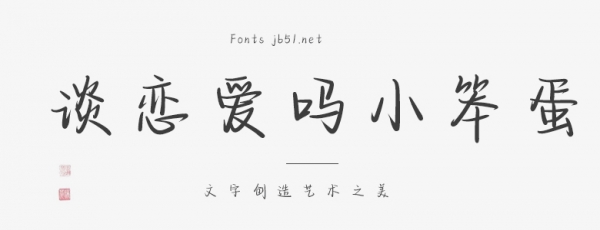
談戀愛嗎小笨蛋字體是一款充滿浪漫與情感的藝術(shù)字體。該字體設(shè)計靈感來源于戀愛中的甜蜜與純真,將每一個字母、符號都融入了溫馨、趣味的元素。 字體線條流暢,字母之間的距離適中,視覺效果舒適。每個字母都帶有柔和的曲線,仿佛戀人的微笑一般甜美。特別地,小寫字母“a”的頂部設(shè)計成了一個小小的愛心,表達出對愛慕之人的深深愛意。 整款字體風(fēng)格清新、俏皮,適合應(yīng)用于各種浪漫、溫馨的場合,如情侶間的書信、禮品包裝、婚禮請柬等。當(dāng)使用這款字體時,能夠為文字增添一份獨特的情感色彩,讓讀者感受到戀愛中的甜蜜與純真。 總的來說,“談戀愛嗎小笨蛋”字體不僅具有優(yōu)美的設(shè)計美感,還能引發(fā)人們對戀愛的美好回憶與憧憬。它是一款集藝術(shù)與情感于一體的獨特字體,適合廣泛應(yīng)用于戀愛相關(guān)領(lǐng)域,為人們帶來浪漫的視覺享受。